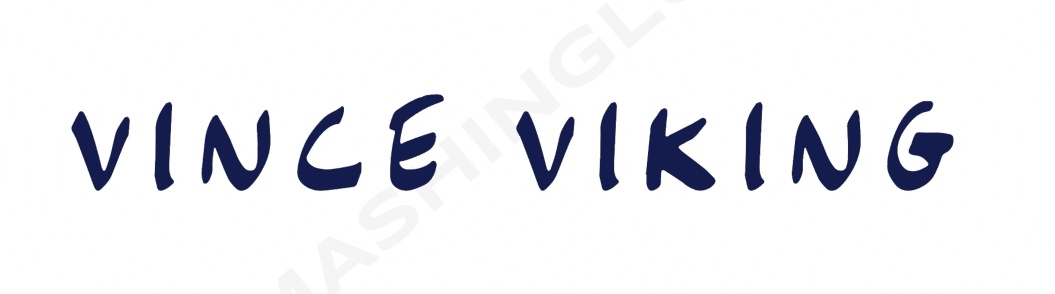
Schriftart Name
kann mir jemand sagen, wie anliegende Schrift heißt?
Ich habe bereits recherchiert und kann sie nicht finden. WhatTheFont u.ä. haben auch nichts komplett stimmiges gefunden.
geh mal auf www.dafont.com
da sind tausende schriftarten. denke dass du unter „cartoon“ oder „comic“ fündig werden könntest.
ich finde Bristle - Hand Drawn Font sehr passend.
Bristle otf (400) ist sehr ähnlich, allerdings sind die Abstände der einzelnen Buchstaben enger.